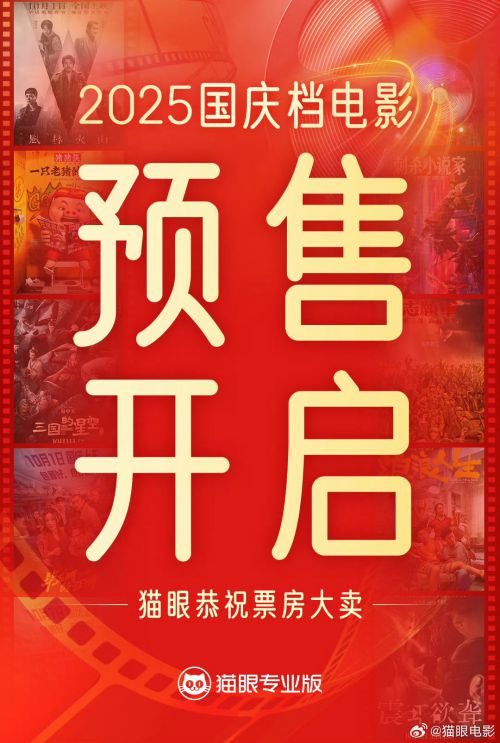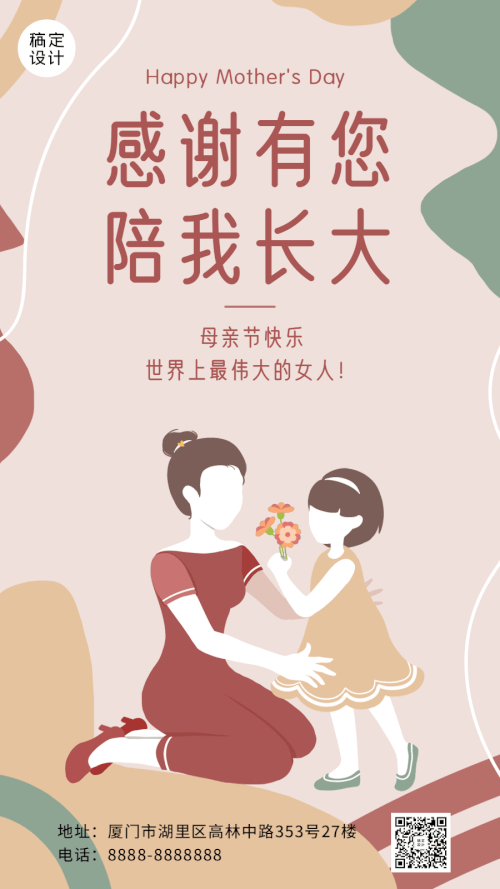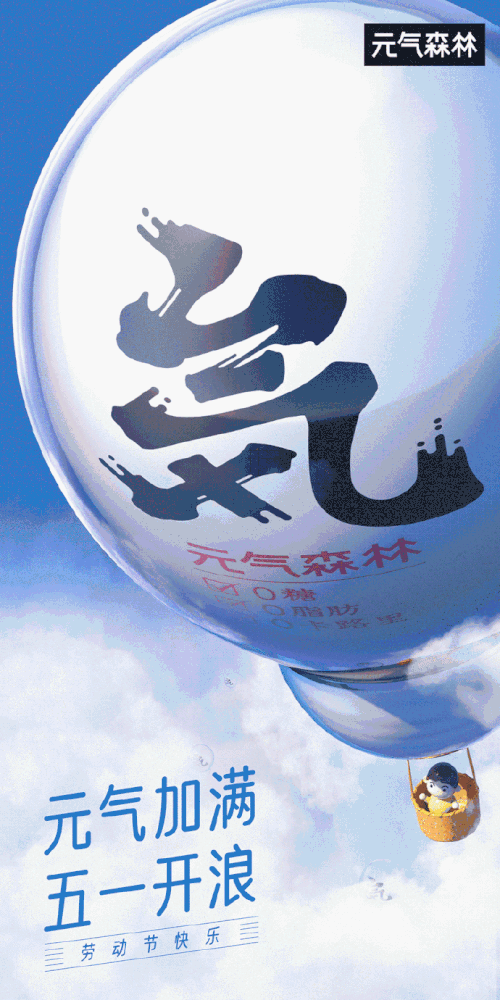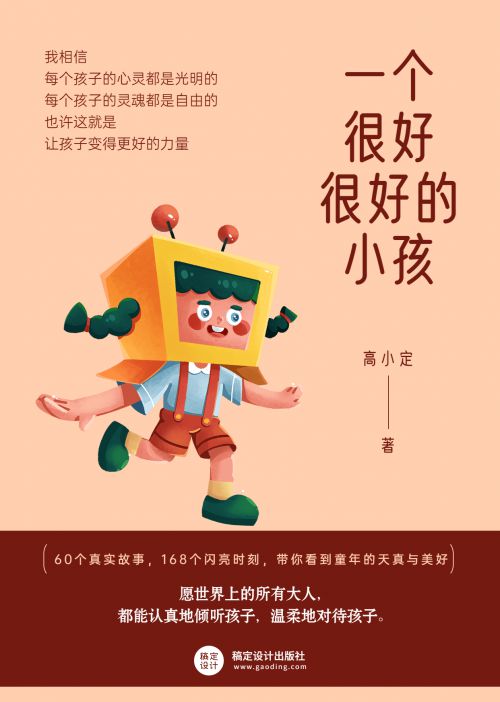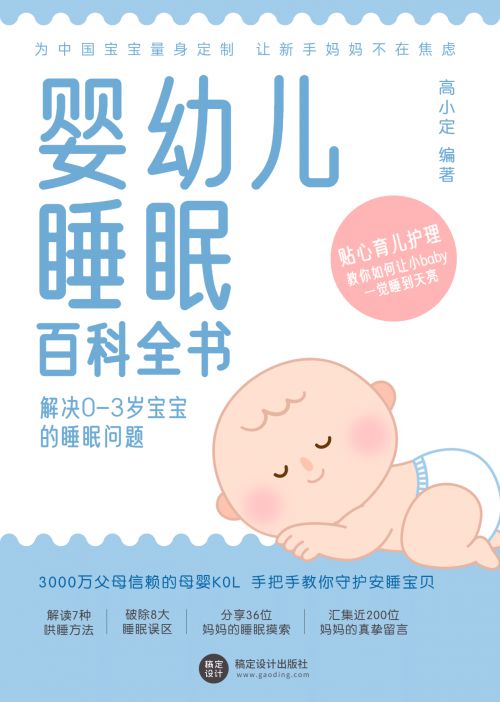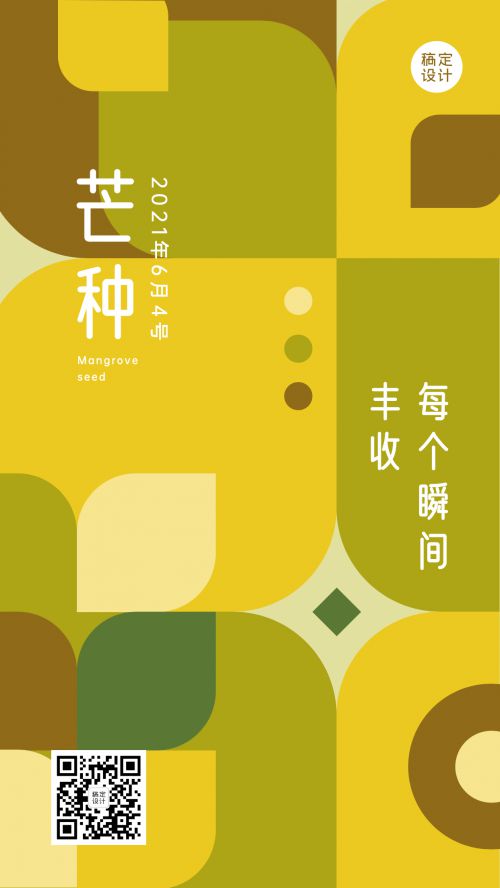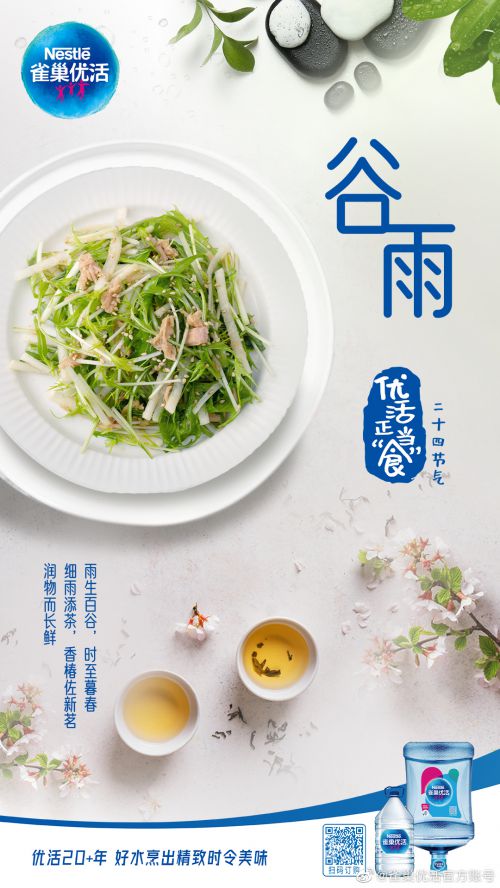
优设好身体
优设好身体是优设字库联合字由发布的第二款免费商用圆体字体,以现代简约风格为核心设计理念,授权范围覆盖全场景免费商用,满足个人与企业的多样化设计需求。 优设好身体字形方正稳健,重心居中且中宫适中,既保持了圆体的柔和特质,又通过方正结构增强了视觉稳定性,阅读体验清晰流畅。字体在笔型设计上融入细腻圆角处理,笔画粗细均匀且端头呈圆头形态,整体观感圆润亲和,打破传统圆体的臃肿感;笔画间多采用断开连接设计,避免繁复缠绕,让字体在保持柔和感的同时更显清爽利落,细节处尽显设计巧思。 无论是海报标题、UI界面排版,还是社交媒体配图、电商Banner设计,优设好身体均能以其简约而不失温度的视觉语言,传递轻松友好的设计氛围,是现代设计中兼具实用性与美感的优质免费商用字体选择。